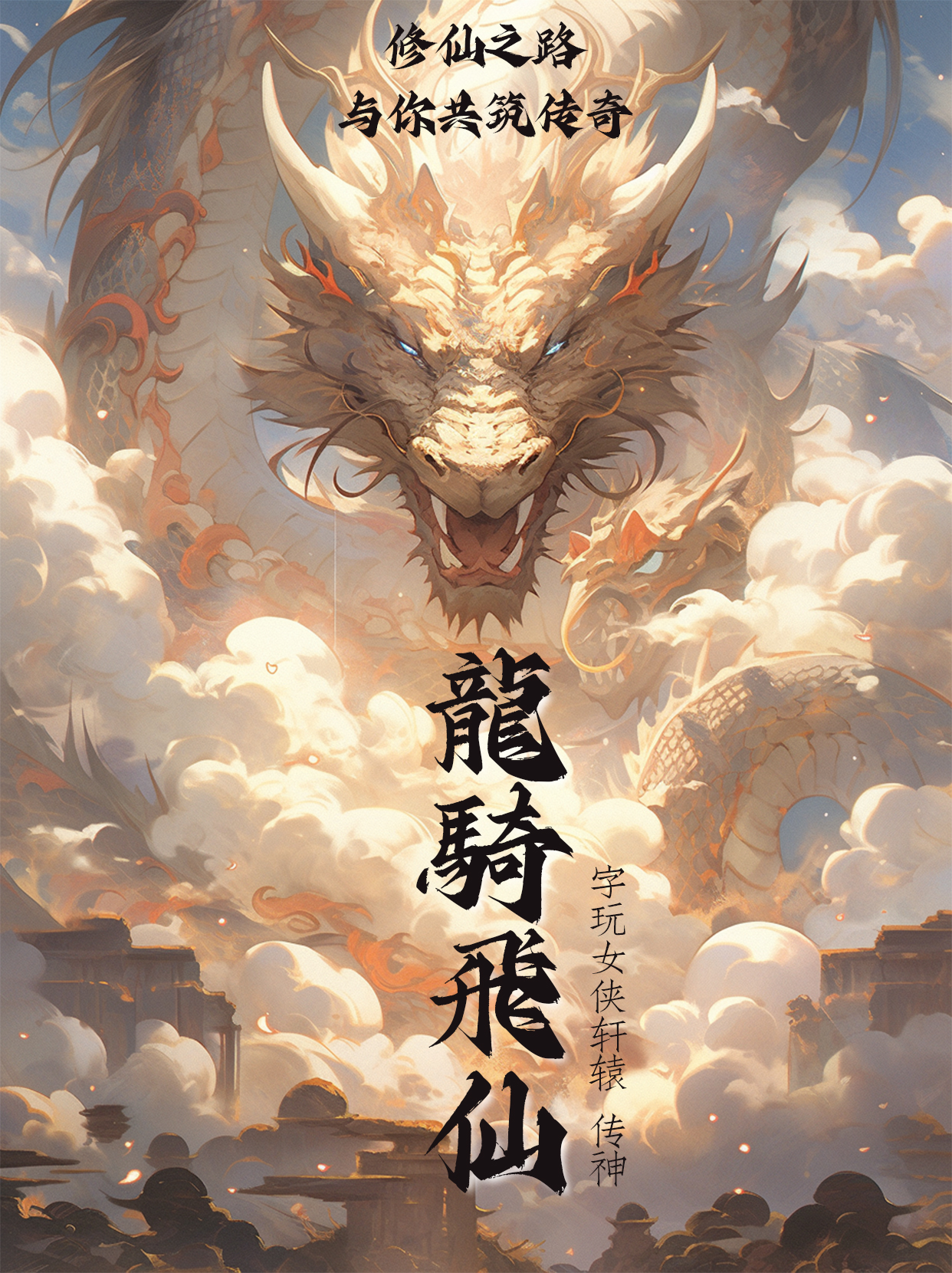
字玩女侠轩辕 传神
Joyfonts-XuanyuanGBT Bold
字体名称:
字玩女侠轩辕 传神
字体语言:
简繁
书体类型:
毛笔字体
字体类型:
普通字体
字体字重:
大黑(Bold)
字玩女侠轩辕 传神
字样介绍
整体结构严谨,笔画堆叠有秩。用笔刚硬却不失灵活洒脱,整体方劲有力,出锋爽利,运用笔画间的牵丝连带丰富字体风格。